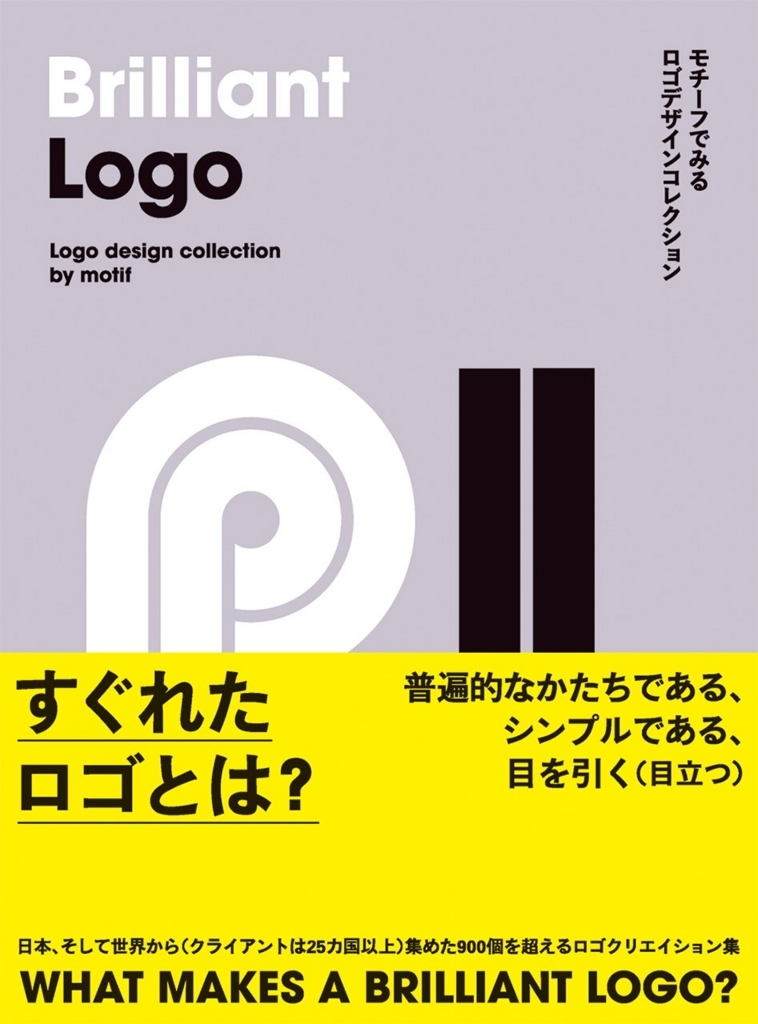
Brilliant Logo - モチーフでみるロゴデザインコレクション
世界中のロゴ900種類以上のロゴを集めたロゴクリエイション集「Brilliant Logo - モチーフでみるロゴデザインコレクション」がビー・エヌ・エヌ新社から2017年8月28日に発売された。
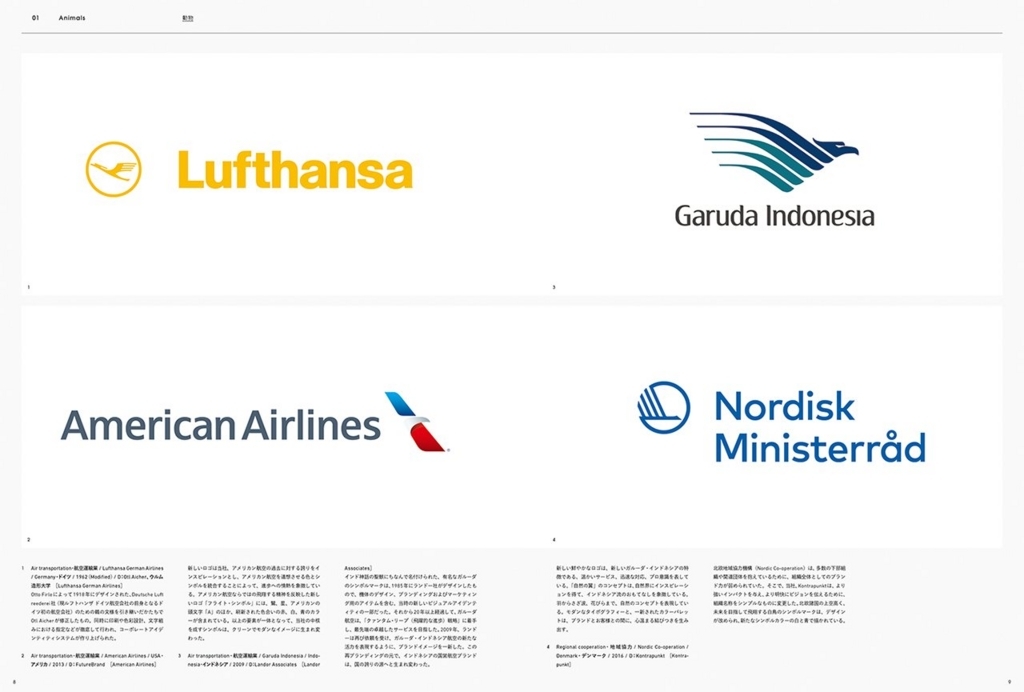
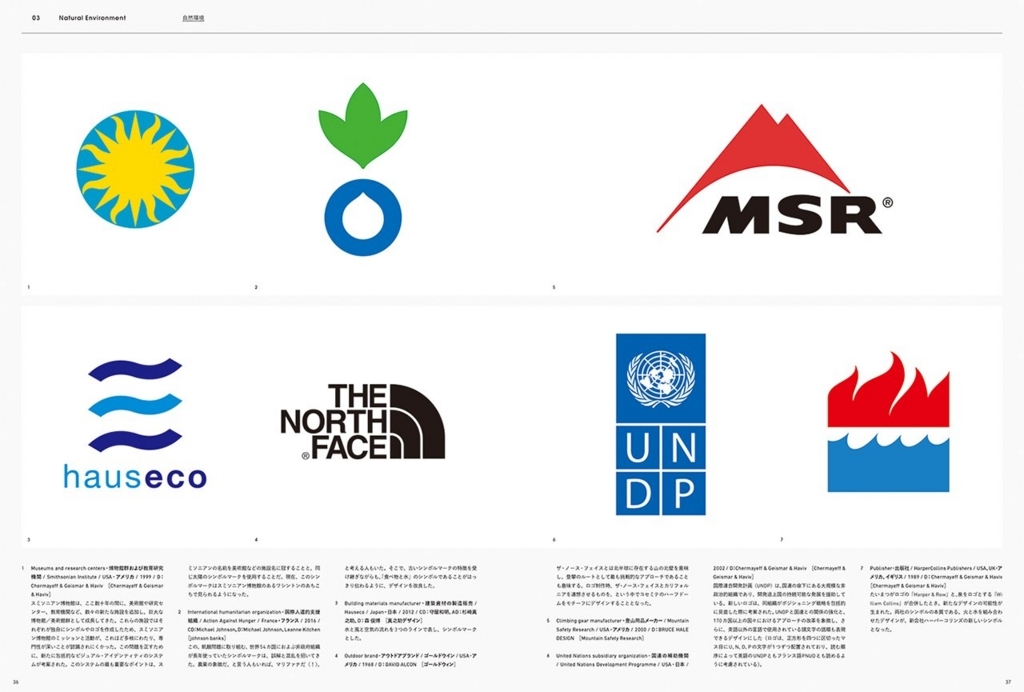
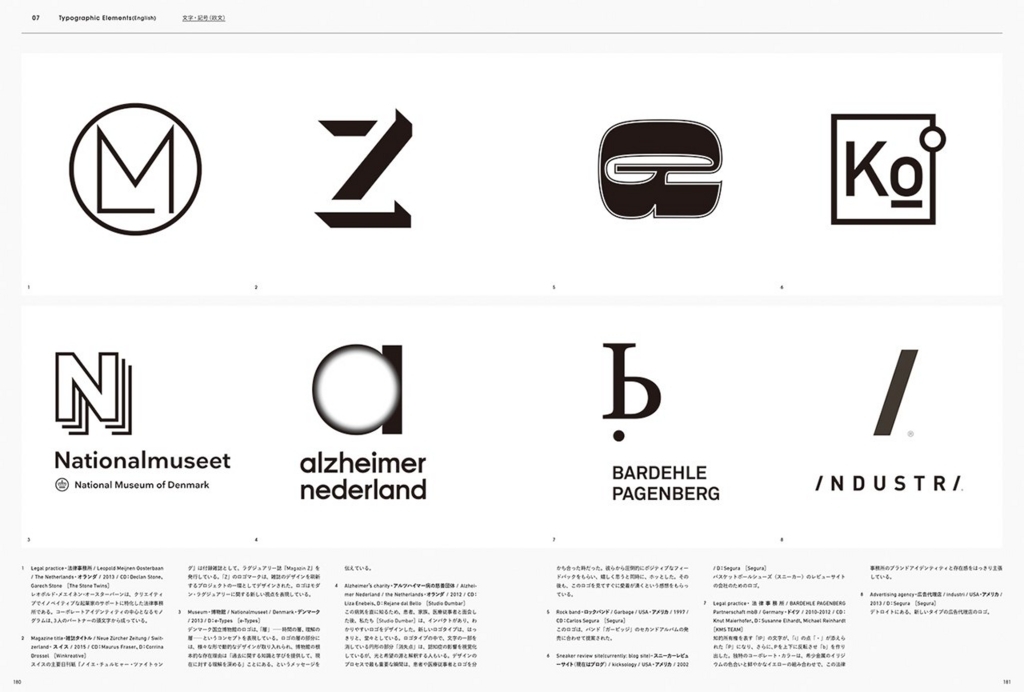
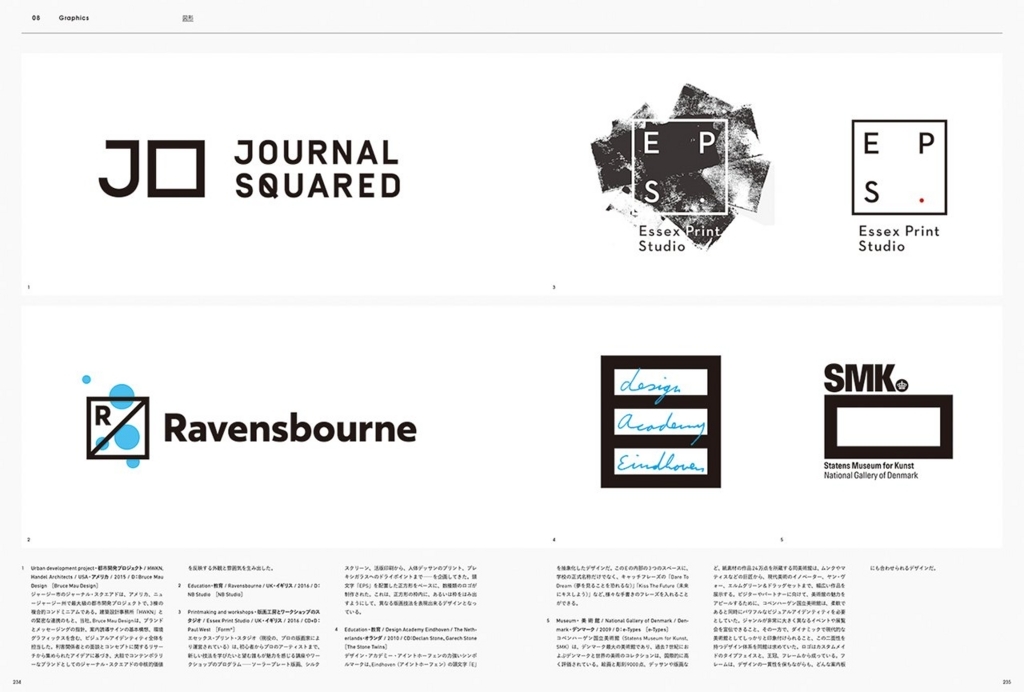
すぐれたロゴとは一体何を指すのでしょうか?
本書は、日本からそして世界から選んだ素晴らしいロゴを、
その形を10のカテゴリーに分けて紹介する事例集となります。
少しずつ修正を加えられながら長く使われ続けられているもの、
ぱっと見て目を引くもの、シンプルなもの。
こうしたロゴの基本を備えたものを集めるとともに、
そのロゴの制作に関する考え方やコンセプトもできる限り掲載しています。
そこから、一体どういった変遷をたどってこのロゴの形ができあがったのか、
どういった思いでつくられたロゴなのか、などさまざまなことが見えてきます。
これらは、新規でロゴをつくらなくてはならない場面において、
強いコンセプトや自由な発想という点でとてもよい手本になるでしょう。
【目次】
01 動物/Animals
02 植物/Plants
03 自然環境/Natural Environment
04 ボディ・ボディパーツ/Body and Body Parts
05 フード/Foods
06 文字・記号(和文)/Typographic Elements(Japanese)
07 文字・記号(欧文)/Typographic Elements(English)
08 図形/Graphics
09 構造物/Constructions
10 日用品・ツール/Everyday Items